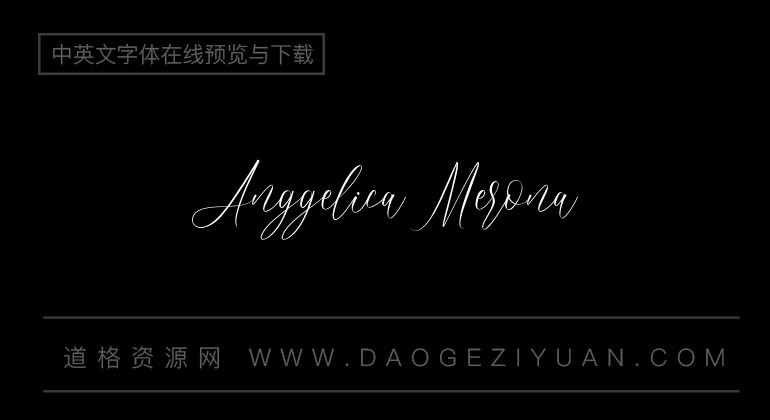
? Anggelica Merona 字体是一款非常特别的英文字体,它的特点是粗细分明,字形清晰,且有较强的空间感,能够更好的把握空间的分布。它的字体特点是粗细分明、字形清晰,且有较强的空间感,可以更好的把握空间的分布,是一款非常适合用于广告、商标、标志、报刊杂志、书籍、电脑屏幕显示等场合的字体。内容介绍
Anggelica Merona是一款非常不错的手写艺术字体,具有很好的视觉感,适合于文化类的宣传设计、商业类品牌的广告和产品包装设计以及个性化文字排版等较多场景。